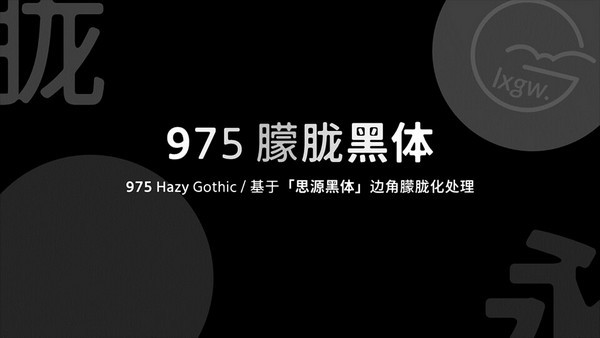
975朦朧黑體讓你的電腦字體別具一格,獨(dú)特的線條加上加黑處理更有剛勁有力的字體表現(xiàn)還有簡(jiǎn)單的安裝方法輕松更換,適合喜歡更換各種字體的朋友十分值得一試。需要的朋友趕緊來(lái)下載吧!
975朦朧黑體是一款基于思源黑體邊角朦朧化處理的字體,朦朦朧朧產(chǎn)生距離美,進(jìn)行邊角朦朧化之后,字體感覺像墨暈開了一樣,產(chǎn)生別樣的感受!